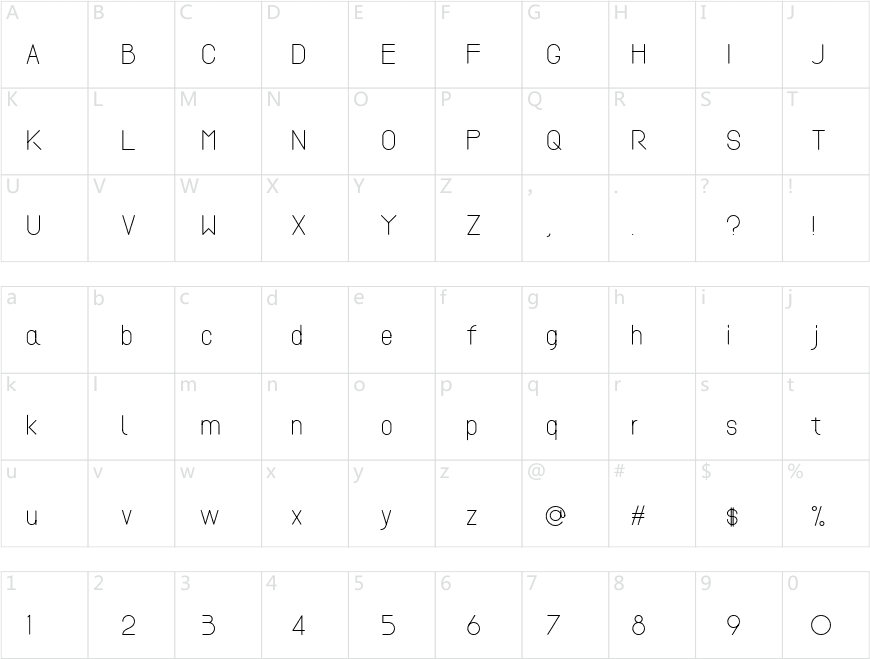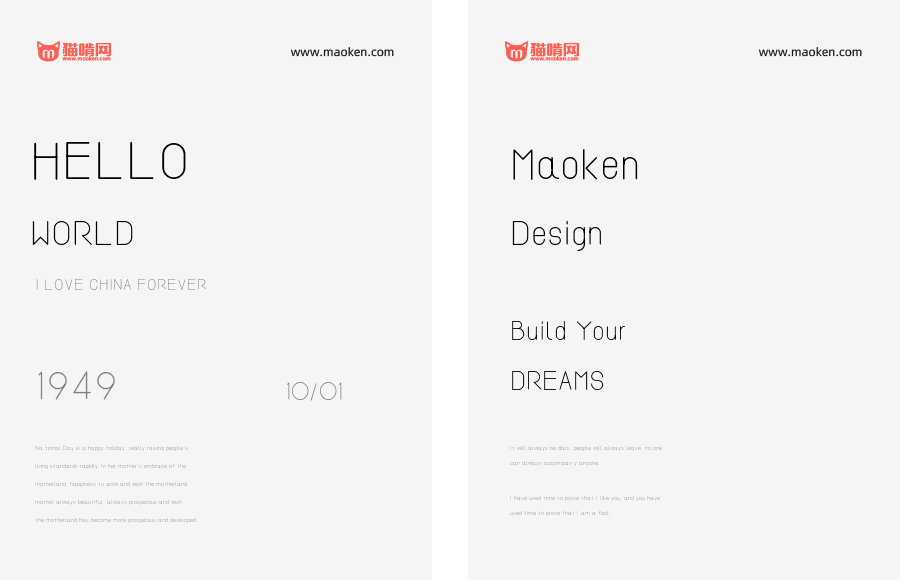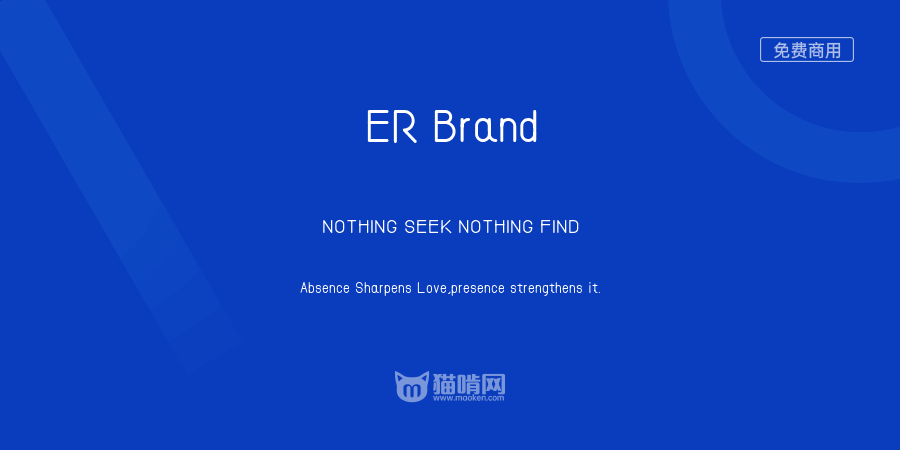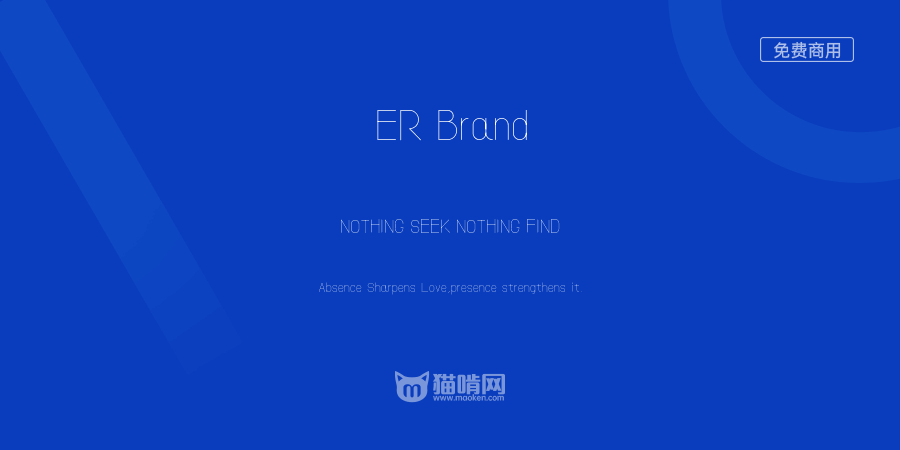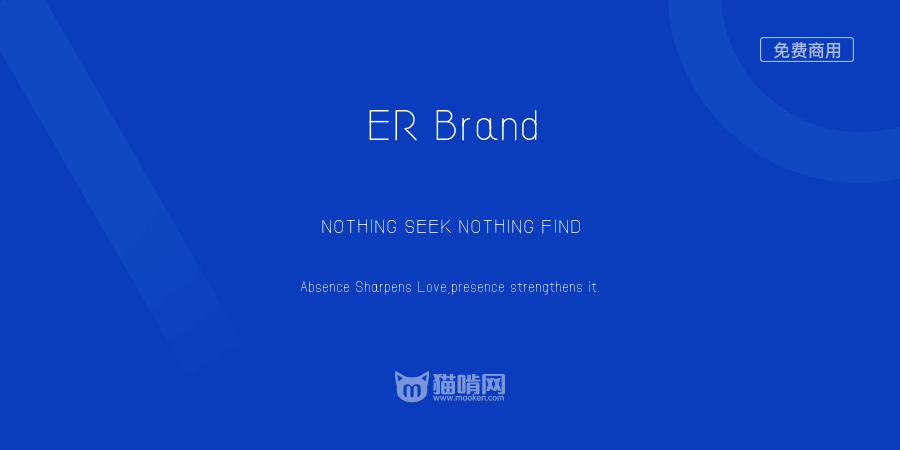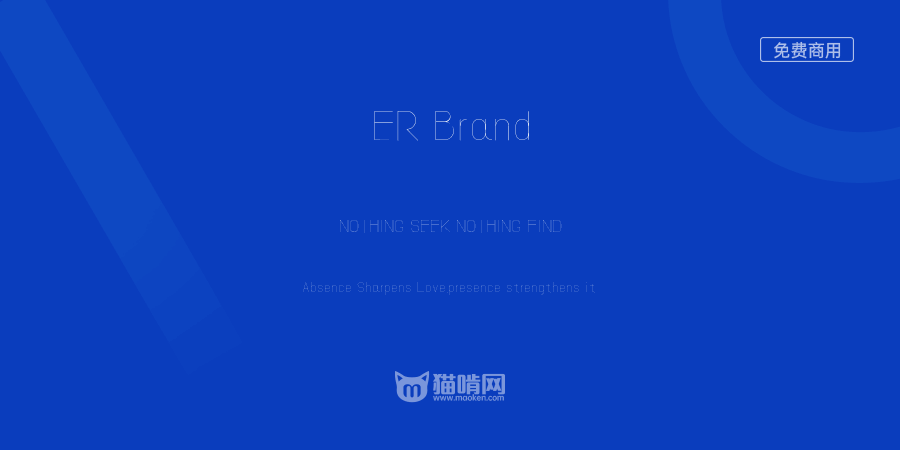
ER Brand
字体作者:非也M007 (中国) 字体字重:4个
这里有26(或许×2\(^o^)/)个字母
我们想要设计一款英文字体来自用,于是经过拆解与重构,根据需求与法则,分别做出来这样26个大、小写字母,现在放上来与大家共同探讨学习下,大家都可以免费下载来使用哦。
早在4月底做完字形(原本只打算做26个大写,后来发现有软件可以制作成字体安装包,于是又做出了小写和数字),但是由于做成字体安装包比较不顺利(刚开始还以为自己学会了新的技能,后来发现想多了),所以我们就一直放着,然后得空就拿出来用PC和MAC不同的字体制作软件来优化下,而导出总是会出现各种问题,就废了差不多2个月才拿出来见人,当然现在还是有问题,但是太费时间,所以暂时就先不调整了,一般使用或是作为标题使用还是不错的。